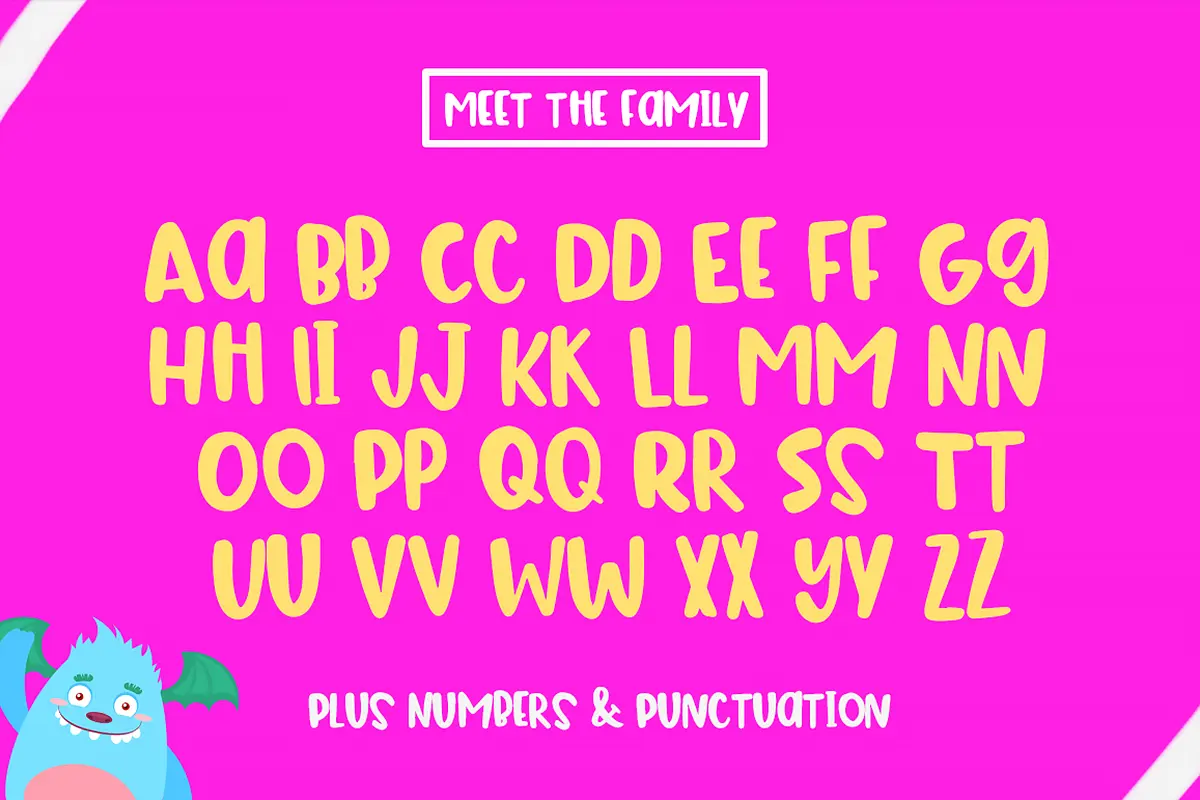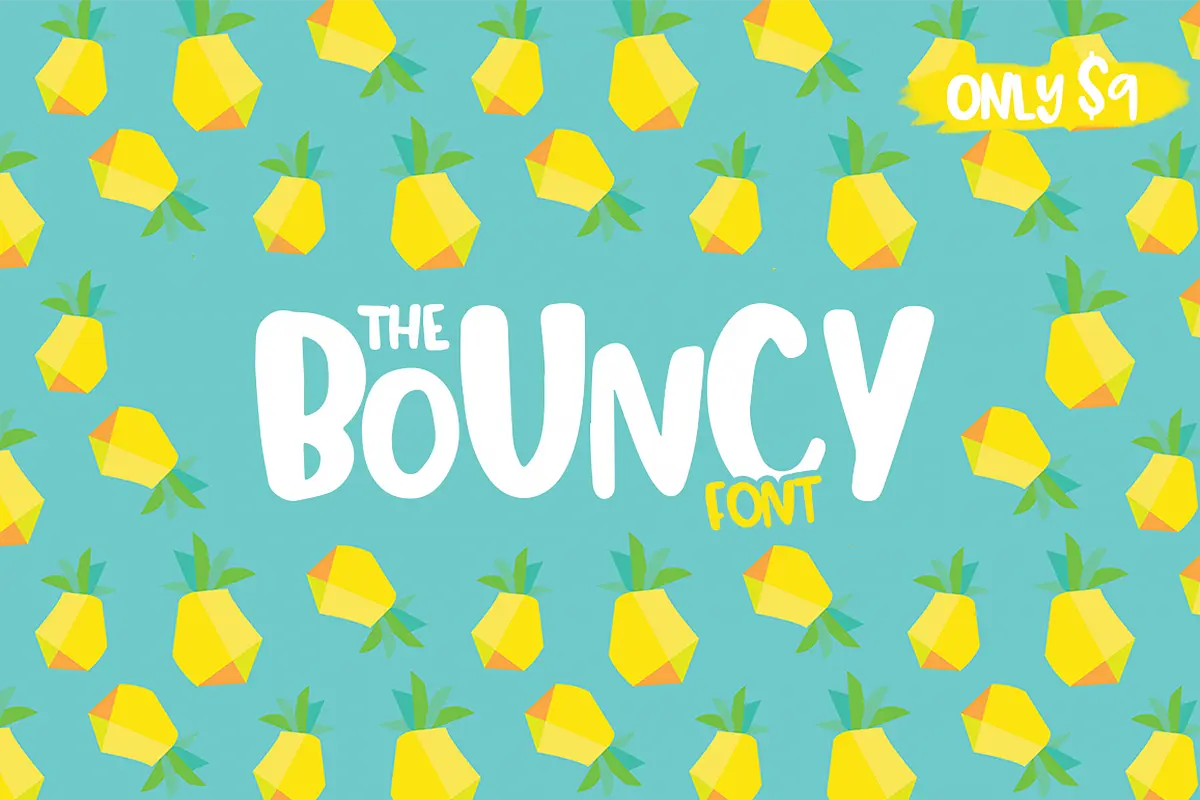
فونت کودکانه و فانتزی
فونت کودکانه و فانتزی Bouncy یک تایپفیس دست نویس و جذاب است که با ظاهر شاد و کودکانهاش برای طراحیهای سرگرمکننده و پرانرژی بسیار مناسب میباشد. این فونت با سبک دستنویس و حالت پرجنبوجوش خود، حس سرزندگی و شادی را به پروژههای گرافیکی اضافه میکند و برای طراحیهای مرتبط با کودکان یا طرحهای دوستانه و صمیمی انتخابی عالی است.
⭐ ویژگیهای محصول
- طراحی دستنویس و پرانرژی
- مناسب برای پروژههای کودکانه و شاد
- افزایش جذابیت در طرحهای روشن و رنگارنگ
- تایپفیس منحصر به فرد با حس دوستانه و صمیمی
🎯 موارد استفاده
- طراحی کتابها و داستانهای کودکانه
- ساخت پوسترهای شاد و رنگی
- استفاده در بستهبندی محصولات کودکانه
- طراحی کارتهای دعوت و تبریک با حالوهوای دوستانه
- افزودن به پورتفولیو طراحان گرافیک برای پروژههای سرگرمکننده